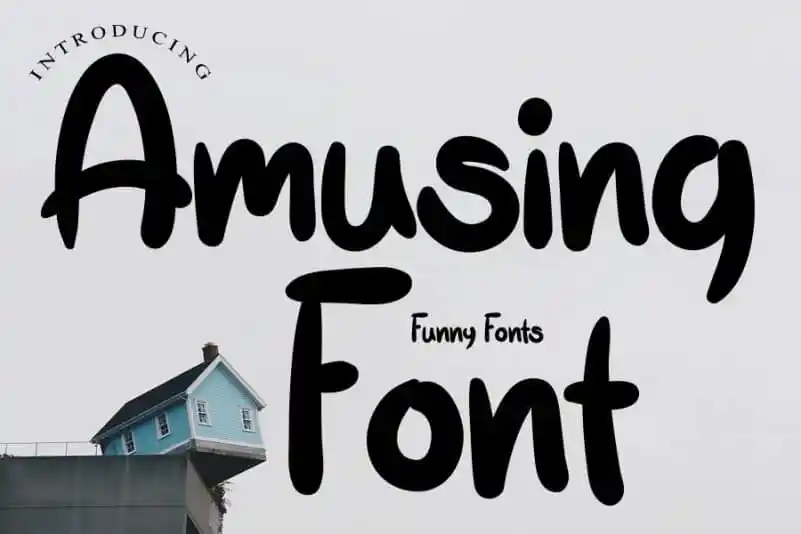
Amusing Display Font – Download Grátis
A fonte ‘Amusing Display Font’ é uma elegante variedade de tipo à mostra que mistura sutileza e audacia ao mesmo tempo. Desenvolvida pelo designer LevinCreative, ela se assemelha a uma escrita manual descontraída e não simétrica. Esta fonte é incrivelmente versátil, capaz de dar um novo boost aos designs mais tradicionais, elevando-os ao nível mais alto. Seja para cartazes de eventos criativos ou websites divertidos, sua capacidade de personalização permite que você crie visualizações atraentes e intrigantes. Essa fonte é perfeita para aqueles que querem adicionar um toque desconcertantemente alegre ao seu trabalho gráfico.